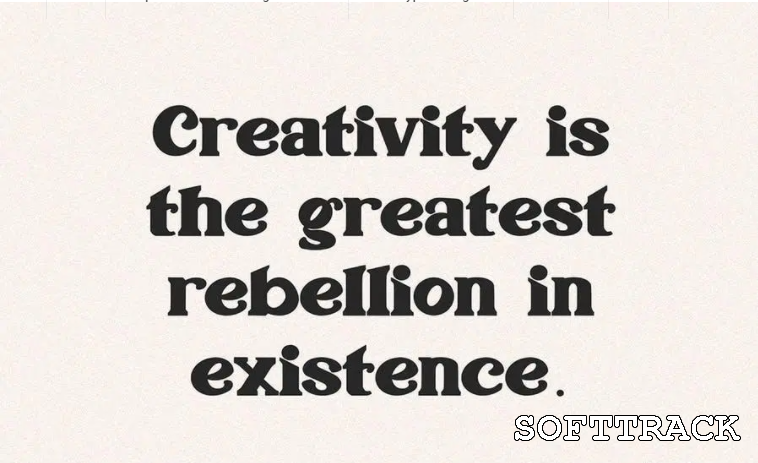
Introductie van een Mintello -
Modern retro lettertype met scherpe en mooie letters die lettertypen creëren die modern, trendy en elegant zijn. Wayfaring kwam met opentype-functies zoals stilistische alternatieven, stilistische sets & amp; amp; ligaturen goed voor logo, poster, badge, boekomslag, t-shirtontwerp, verpakking en meer.
Kenmerken:
• Tekenset AZ • Cijfers en leestekens (OpenType-standaard) • Accenten (meertalige tekens) • Ligatuur • Alternatief